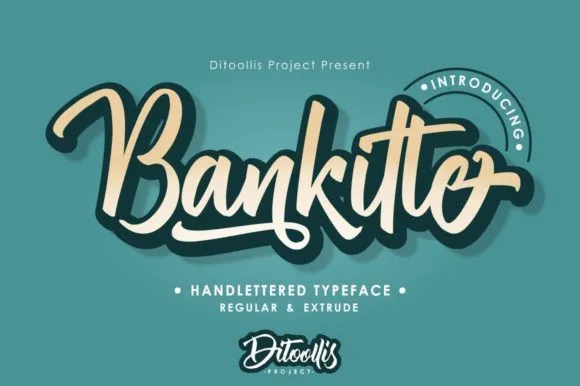
Bankitte Handlettered Font – Download Grátis
Aqui está uma versão em português do Brasil de 2 parágrafos curtos para a descrição da fonte “Bankitte Handlettered Font”: Esta fonte ‘Bankitte Handlettered Font’ é um belo deslizamento de letras com traços robustos, inspirado nas estilos originais de caligrafia. Ela combina influências do hand-lettering para criar uma experiência visual vibrante e dinâmica. A fonte foi criada pela equipe da Ditoollis Project, que também compartilhou a fonte. Com um design elegante e versátil, é perfeita para invesagens, logotipos, cartões de visita, capas e até mesmo para adicionar um toque criativo aos t-shirts ou criar expressões inspiradoras em citações. A fonte é uma ótima opção para designers que buscam dar um toque especial a seus projetos digitais. Com seu design único e atraente, ela pode ser usada de diversas maneiras dentro do design gráfico – seja em aplicações corporativas ou pessoais, sempre garantindo um resultado impecável e estiloso.